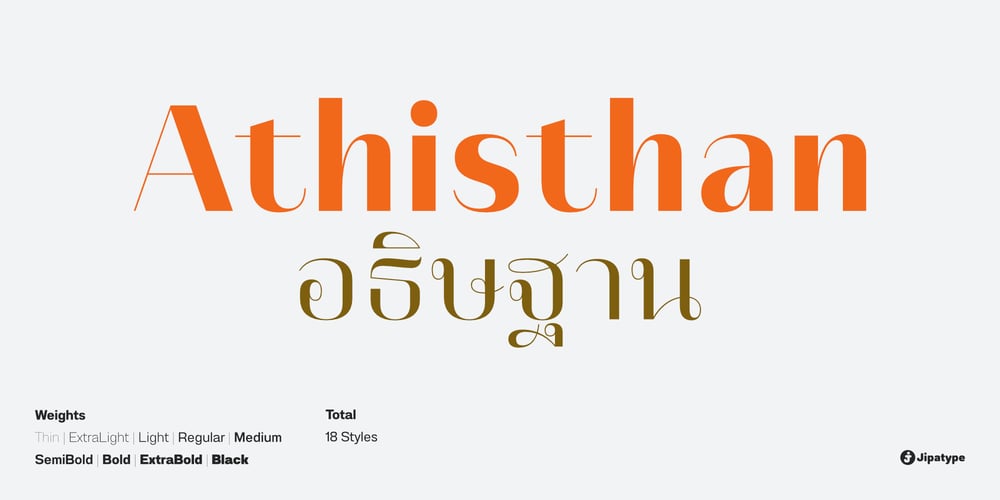
Athisthan Font Family was designed by Anupap Jaichumnan and published by Jipatype. Athisthan contains 18 styles and family package options. อธิษฐาน เป็นอักษรแบบคอนทราสต์แซนส์เซอริฟ มาพร้อมกับอักษรแบบมีหัวสำหรับภาษาไทย ดูทางการ เรียบหรู มีเสน่ห์ เหมาะสำหรับการใช้ผาดหัว หรือรองผาดหัว มีทั้งหมด 9 น้ำหนักและตัวเอียงของแต่ละน้ำหนักรวมทั้งหมดมี 18 สไตล์ และมีฟีเจอร์อื่น ๆ อาทิเช่น Small Caps และฟีเจอร์อื่น ๆ พร้อมให้คุณได้เลือกใช้งาน รองรับหลากหลายภาษาAthisthan is a contrast sans serif typeface with loop head style for Thai character. Formal, elegant, charming look. Suitable for headline and sub-headline. Comes with 9 weights and italics of each weight total 18 styles, and there are features such as Small Caps and many features available for you. Support multi-languages.